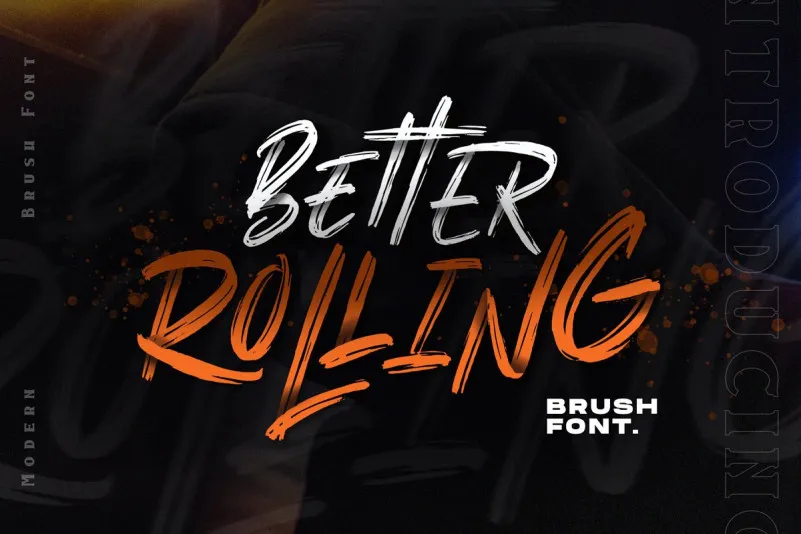
Better Rolling Brush Font – Download Grátis
A fonte ‘Better Rolling Brush Font’ é uma criação de 24Design, que oferece aos designers a oportunidade de trazer para suas criações algo mais autêntico e vibrante com um toque de hand brushing. Esta tipografia de borracha tem imperfeições genuínas do uso da ferramenta à base de pincel seco, característica única que a faz distintiva entre outras fontes de letras de pincel. Perfeitamente complementada por seu par de fonte de pincel, ‘Better Rolling Brush’ oferece uma sensação incrivelmente alegre e movimentada, com um baseline muito flexível que dota o texto de vida. Ideal para uma ampla gama de necessidades de design – desde marcações, logotipos até impressões em produto ou decoração de casa – essa fonte moderna e energética é perfeita para qualquer projeto. Suas caligrafias rapidamente delineadas e detalhes aguçados oferecem um aspecto realista, dando vida aos seus designs. ‘Better Rolling Brush Font’ é certamente a escolha ideal para qualquer tarefa que precise de letras de pincel ou qualquer aplicação em que você deseje adicionar uma mão-dada sofisticada ao seu design.